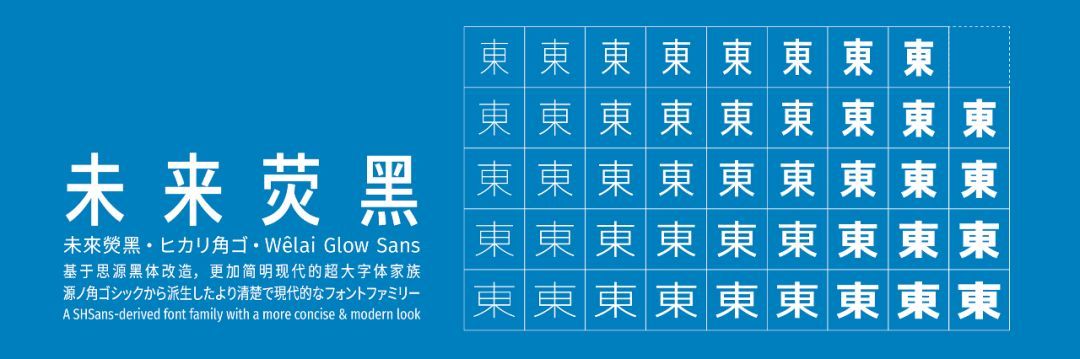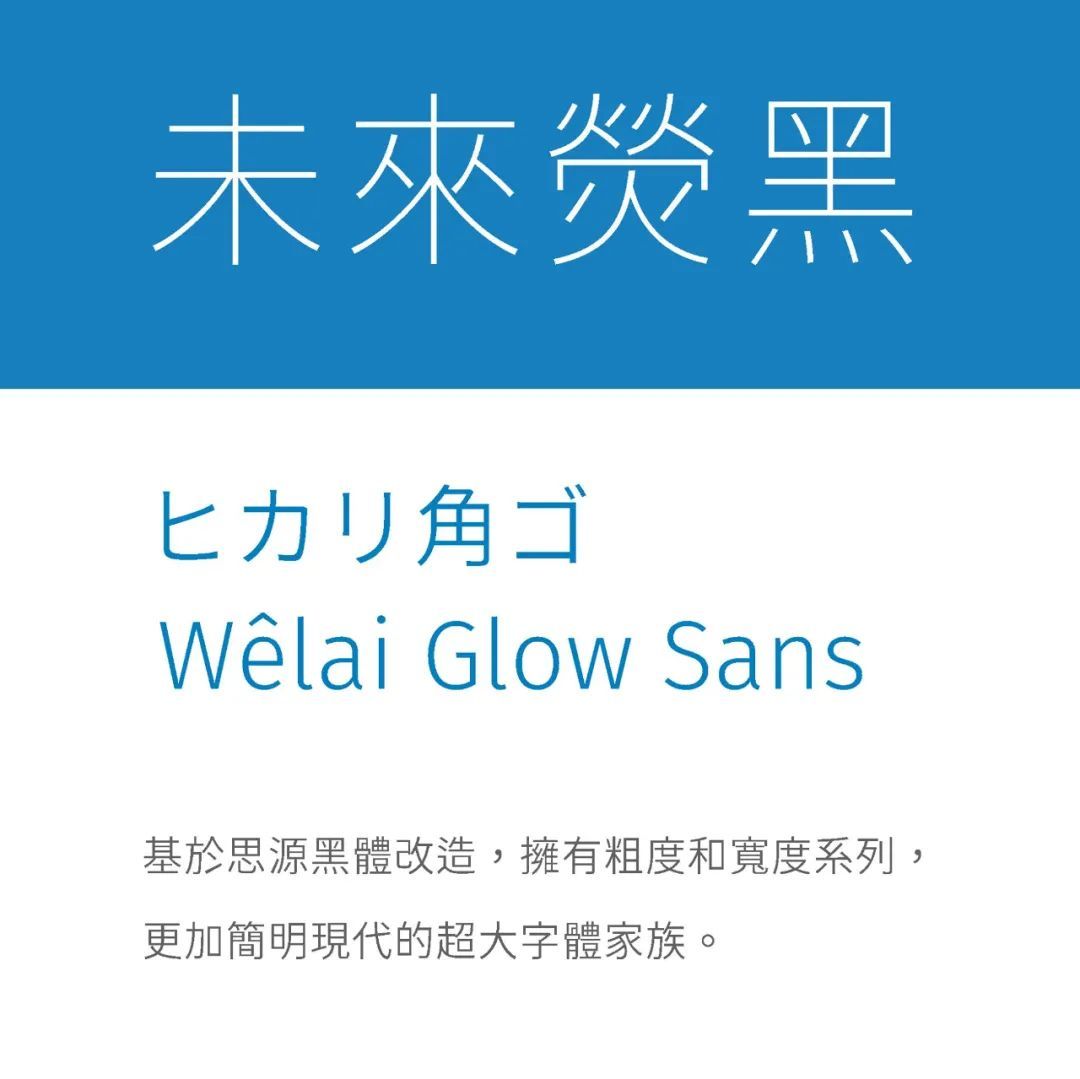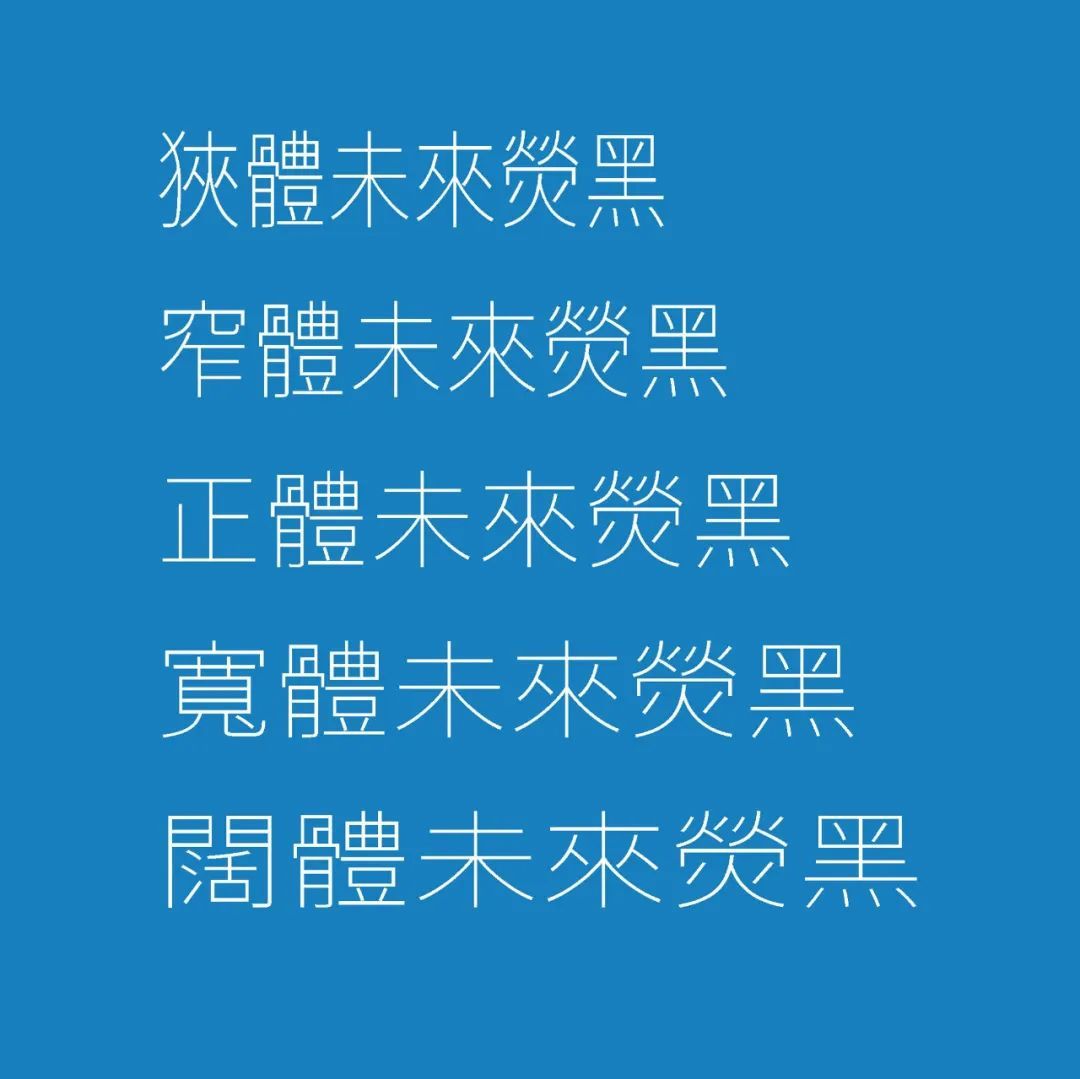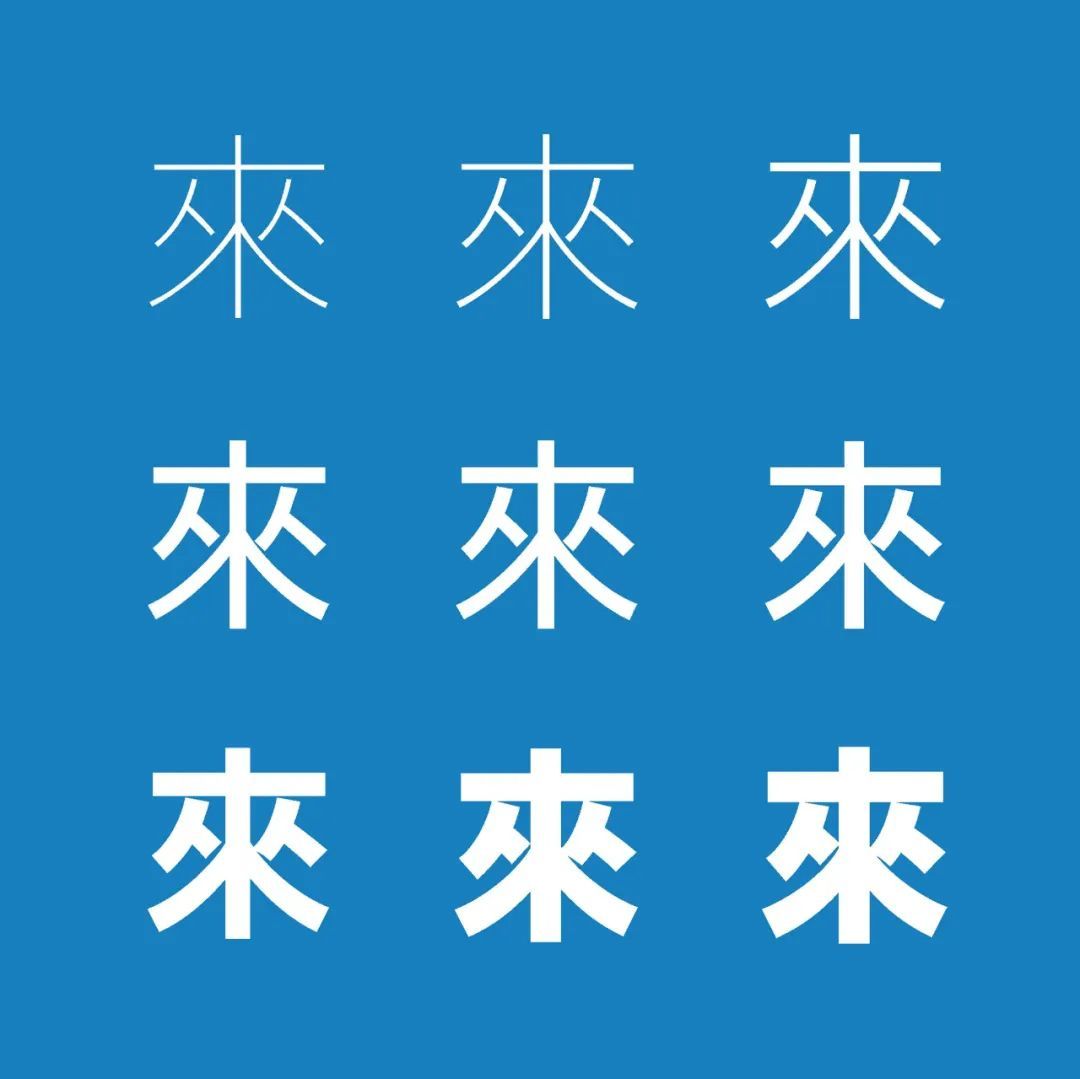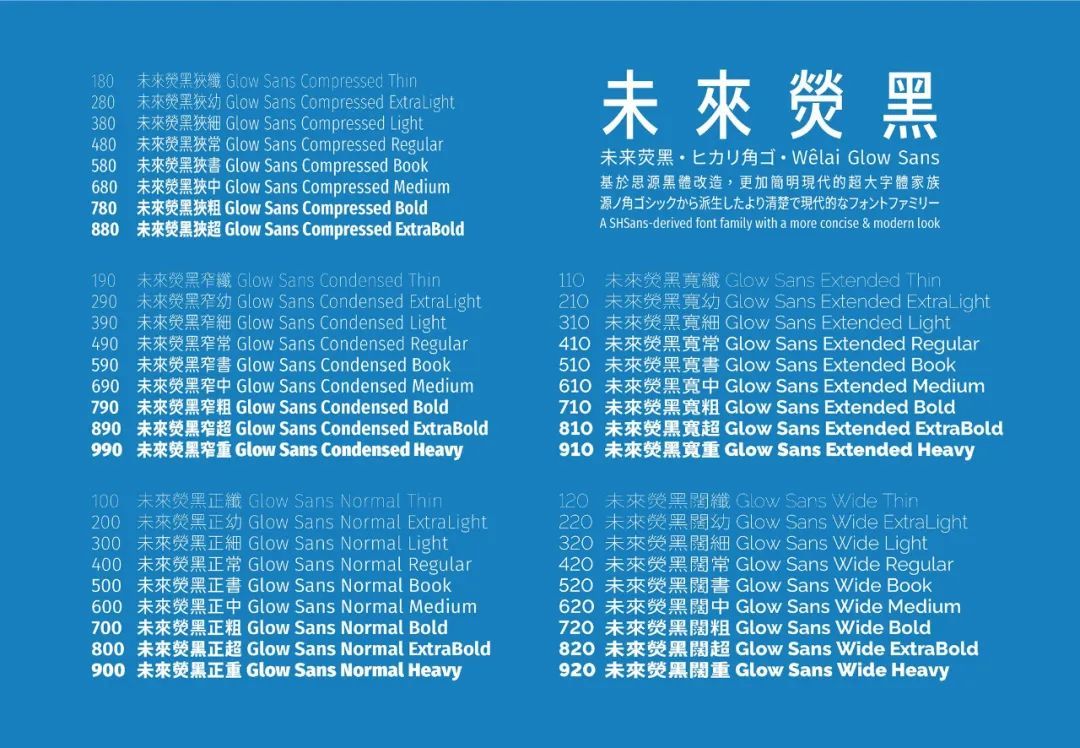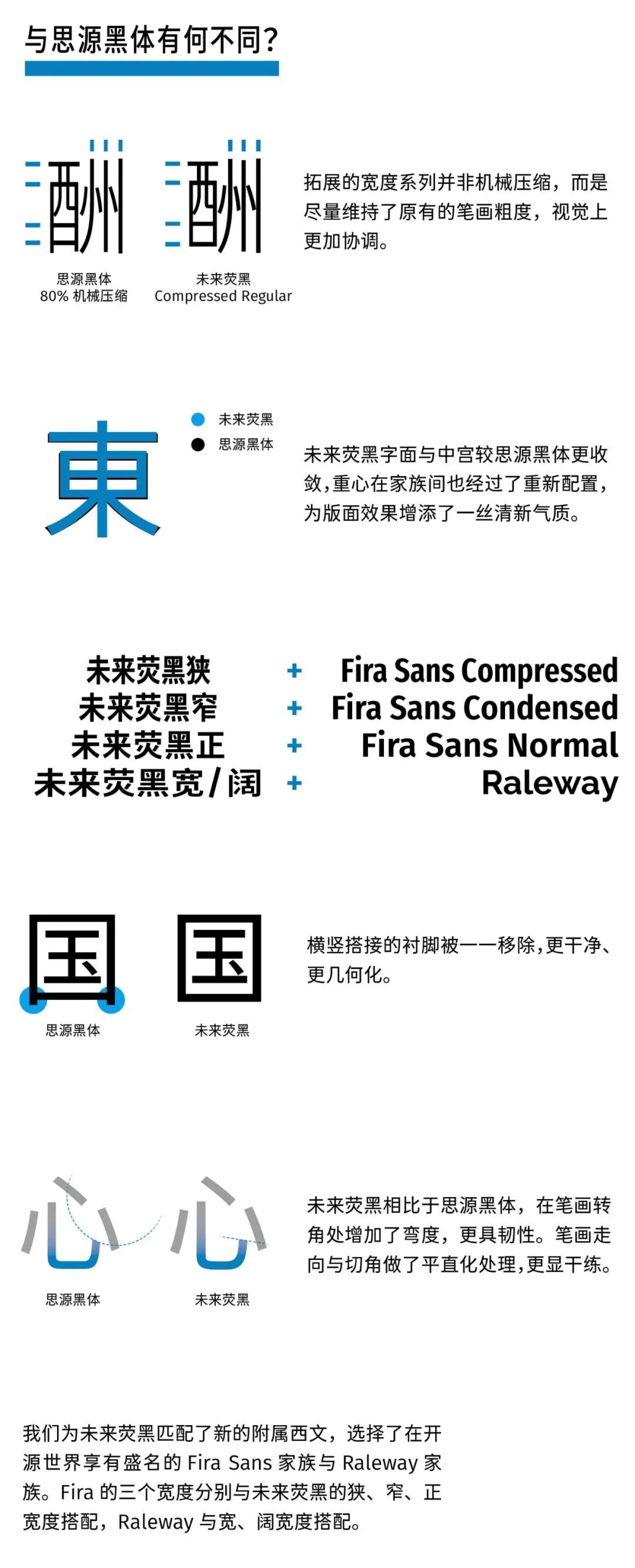
未来荧黑是一个基于思源黑体、Fira Sans和Raleway的开源字体项目,支持简体中文、繁体中文与日文;思源黑体的7字重被扩展为9字重,并提供了宽度系列,全家族共44款字体。
相比于思源黑体,未来荧黑的造型更加简明现代,版面效果清新轻快。未来荧黑的中宫与字面更加收敛,重心在字重之间经过了重新配置;笔画细节上处理得更加干练,简洁而平直化。您可以下载样张来预览未来荧黑的设计。
未来荧黑的实现介于参数化与轮廓滤镜,使用了图像处理算法对字形建模。字体的制作并没有借助字体设计软件,而是用一个Web实现的可视化调参工具来确定字体参数。
思源黑体的7种字重被扩展为9种字重,并增加了5种字体宽度,全家族共包含44款字体。
与思源黑体有何不同?
相比于思源黑体,未来荧黑的造型更加简明现代,版面效果清新轻快。未来荧黑的中宫与字面更加收敛,重心在字重之间经过了重新配置;笔画细节上处理得更加干练,简洁而平直化。
为未来荧黑开发了一个在线演示,同时它是未来荧黑修改字体参数的可视化交互环境。你可以在这里通过改变各种参数来修改文字样貌,导出的参数可用于字体构建。